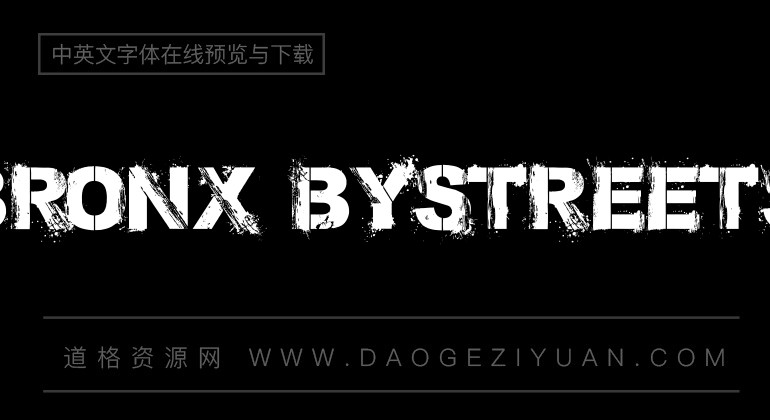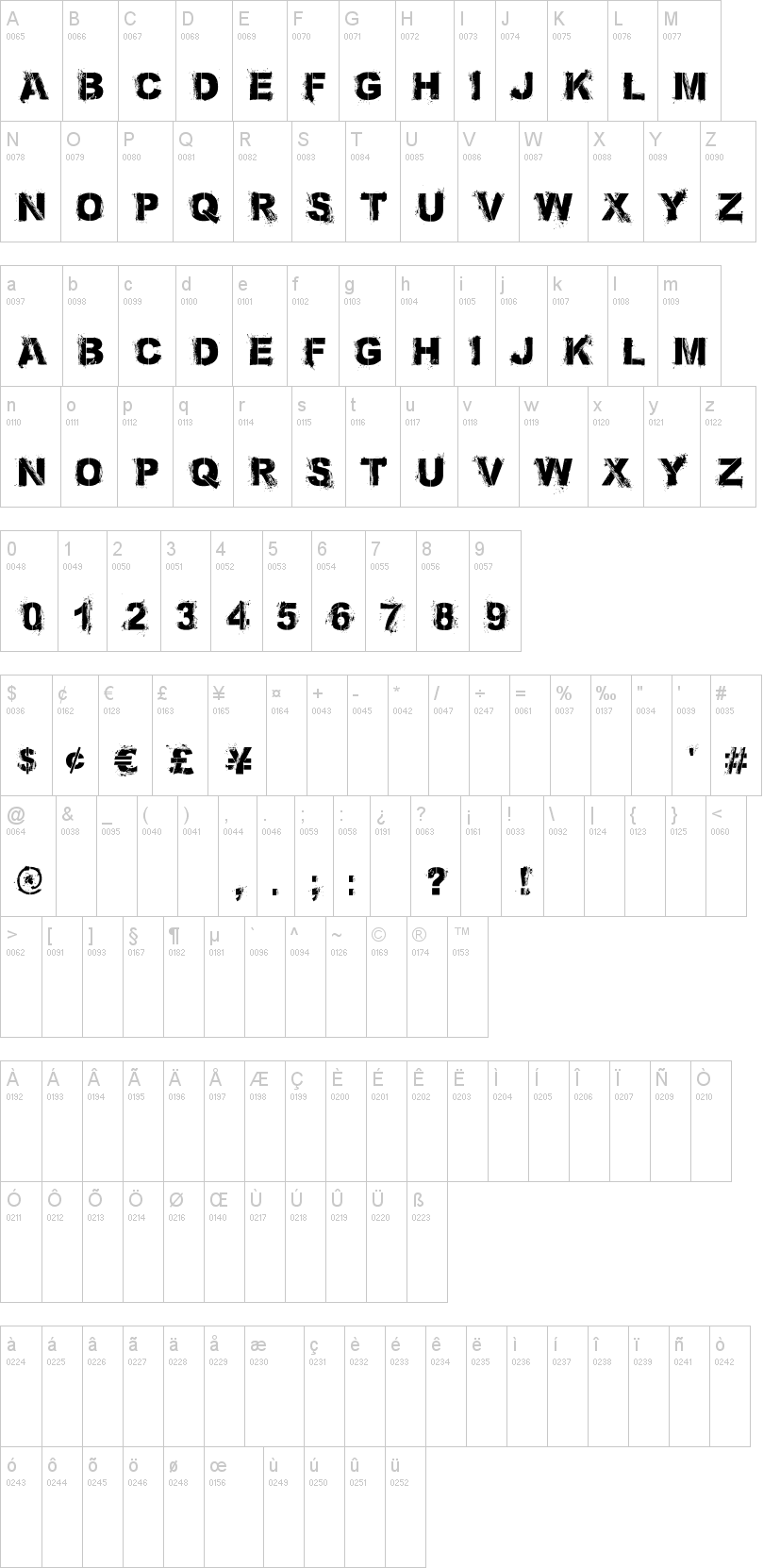
Bronx Bystreets 字体是一款由 Fontry 发布的免费字体,灵感来源于纽约布朗克斯区的街道标志和涂鸦艺术。该字体具有手工制作的感觉,同时也适用于现代设计。 Bronx Bystreets 字体包括大写字母、小写字母、数字和标点符号,支持多种语言包括英语、法语和西班牙语等。该字体的风格独特,具有浓厚的街头艺术气息,可以用于海报、标志、社交媒体、印刷品等多种设计场景。 总体来说,Bronx Bystreets 字体是一款非常酷炫的字体,具有很强的视觉冲击力,适合需要突出特色和个性的设计。内容介绍
Bronx Bystreets是一款非常不错的手写艺术字体,具有很好的视觉感,适合于文化类的宣传设计、商业类品牌的广告和产品包装设计以及个性化文字排版等较多场景。